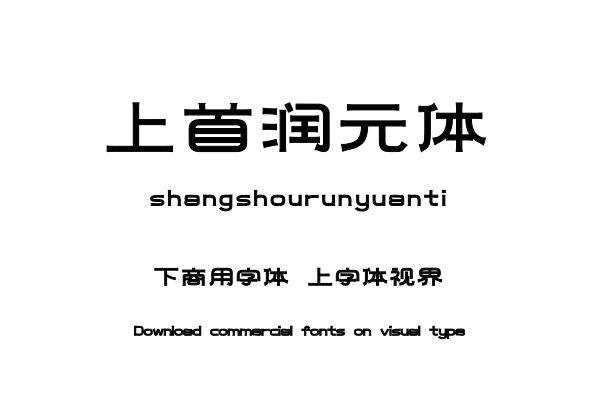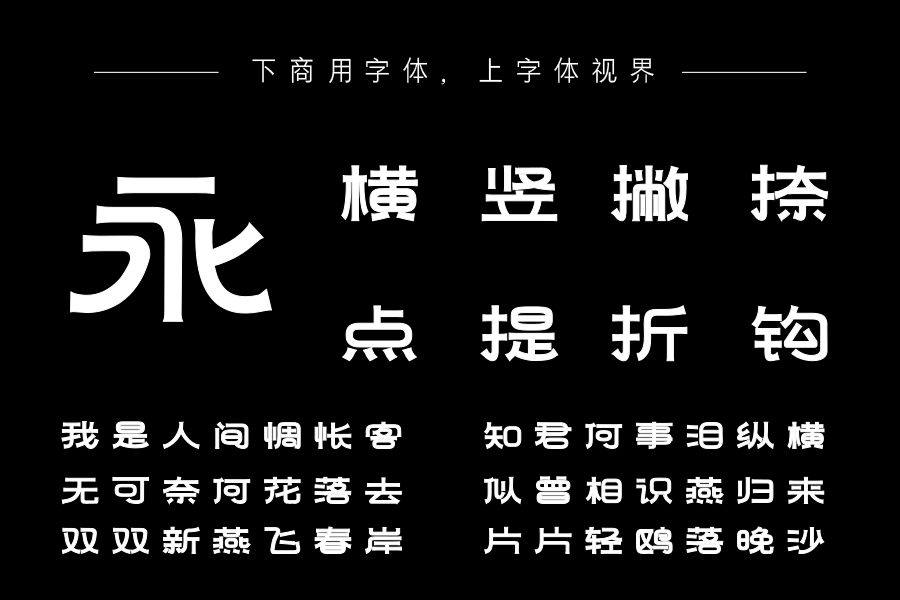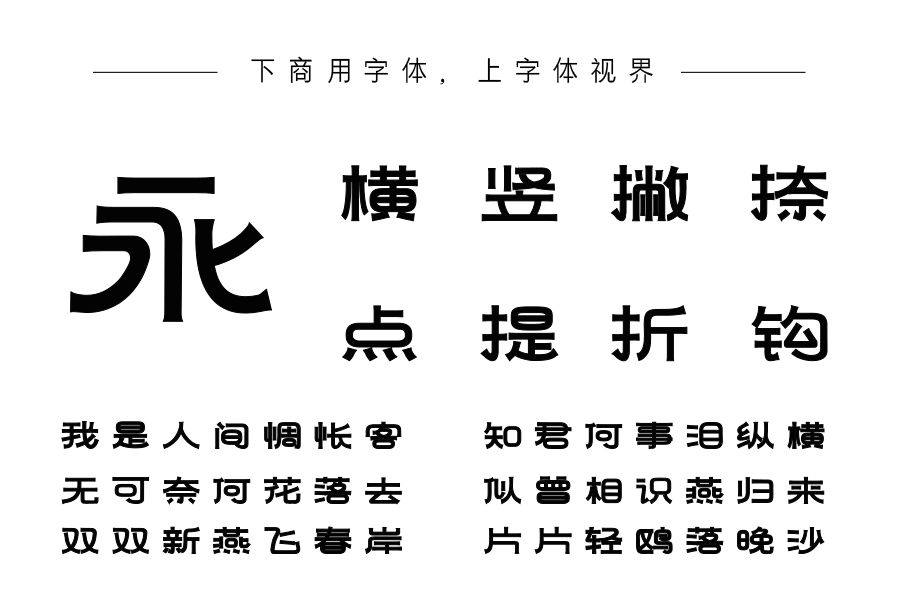
上首润元体,字体笔画圆润可爱有个性。笔画粗细一致,使得字体整体更加统一。字整体形态富有创意,在字体末端增加了幅度变化,同时在字形上也有着创新,这让字体更加具有辨......购买须知:“下载服务费”与“字体VIP”所获得字体 仅用于个人非商用, 商用请联系付费授权。本字体为电脑用字,手机没有root权限不支持直接手机换字(手机如何root,请自行百度搜索教程)。购买前请先 了解清楚后再付款 ,字体为虚拟产品无法回收 一旦购买不支持退款。